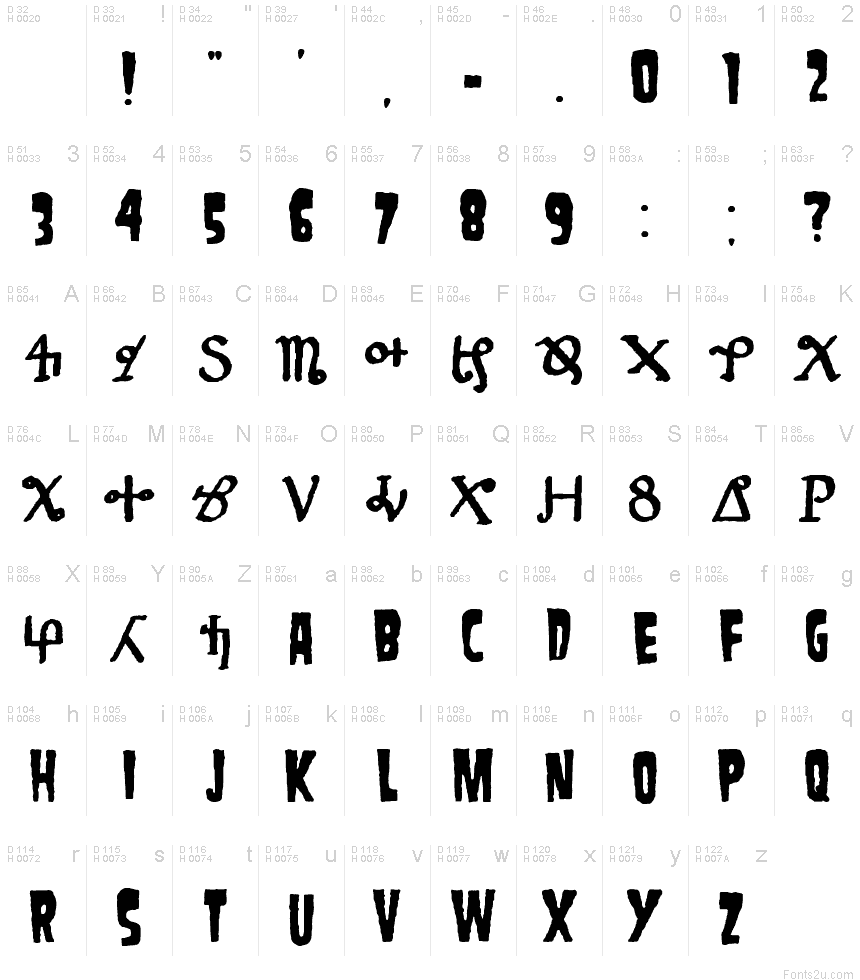
خط Danzig 4p من تصميم Rob Villareal هو خط مجاني مشوه يتميز بطابع خام ومُلطخ بالحبر. تبدو كل حرف وكأنه ممزق يدويًا ومسحوب عبر الصفحة، مع صور ظلية خشنة وحواف غير متساوية تبدو وكأنها خارجة مباشرة من ملصقات الحفلات الموسيقية أو المجلات المغمورة (Zine). تخلق الأشكال المكتنزة والكتلية سطرًا نصيًا ثقيلًا ومحكمًا يصرخ بالضجيج والتمرد على الفور.
يتألق هذا الخط المجاني في عناوين الرعب، وأغلفة ألبومات البانك والميتال، ومنشورات الـ DIY، وتصاميم الهالوين، وعناوين المجلات المغمورة، وشعارات الألعاب ذات طابع الجرنج. استخدم Danzig 4p بأحجام كبيرة وجريئة لتترك الأشكال الملطخة والمسننة تتنفس حقًا؛ قم بإقرانه بخط "سانس سيريف" نظيف ومكثف للنص الأساسي للحفاظ على مقروئية التصميم بينما يتولى العنوان كل الصخب.